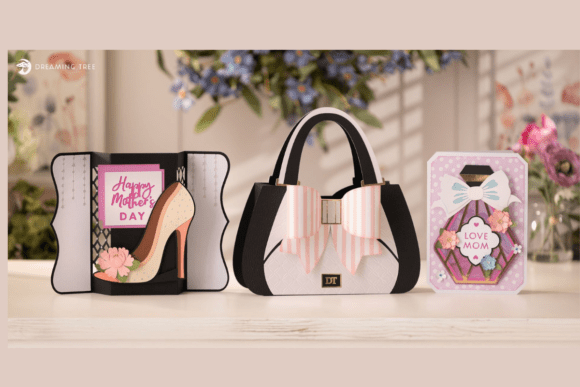
Chic Boutique SVG Bundle
Chic Boutique SVG Bundle gibi yüksek kaliteli varlıklar arıyorsanız, bu premium paket yaratıcı projeleriniz için harika bir seçimdir.
Hassasiyetle hazırlanan Chic Boutique SVG Bundle, temiz vektörler, pürüzsüz tipografi ve içinizin rahat etmesi için ticari bir lisans sağlar.
İster İsteğe Bağlı Baskı (POD) ürünleri, ister düğün davetiyeleri veya sosyal medya grafikleri oluşturuyor olun, Chic Boutique SVG Bundle ideal bir uyumdur.